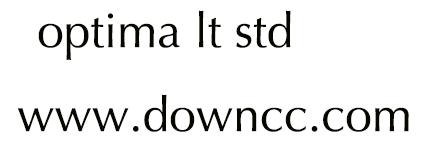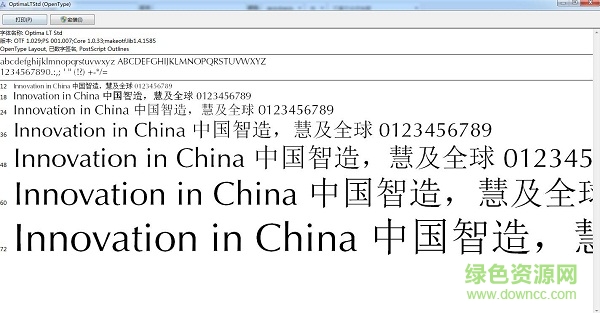
optima lt std roman
optima lt std字體包有optima lt std roman和optima lt std medium兩款,字體線條流暢,細(xì)節(jié)精致,整體優(yōu)雅好看,適用于電子排版或是平面設(shè)計(jì),喜歡的朋友快來(lái)下載吧!